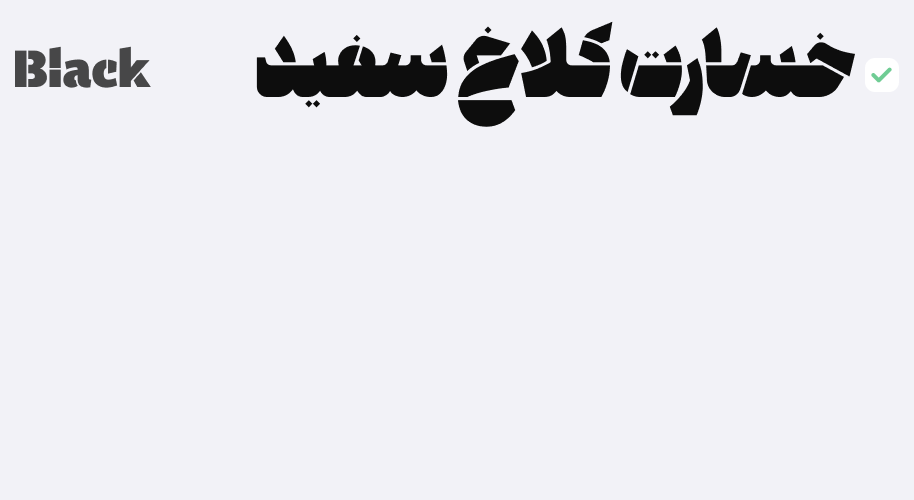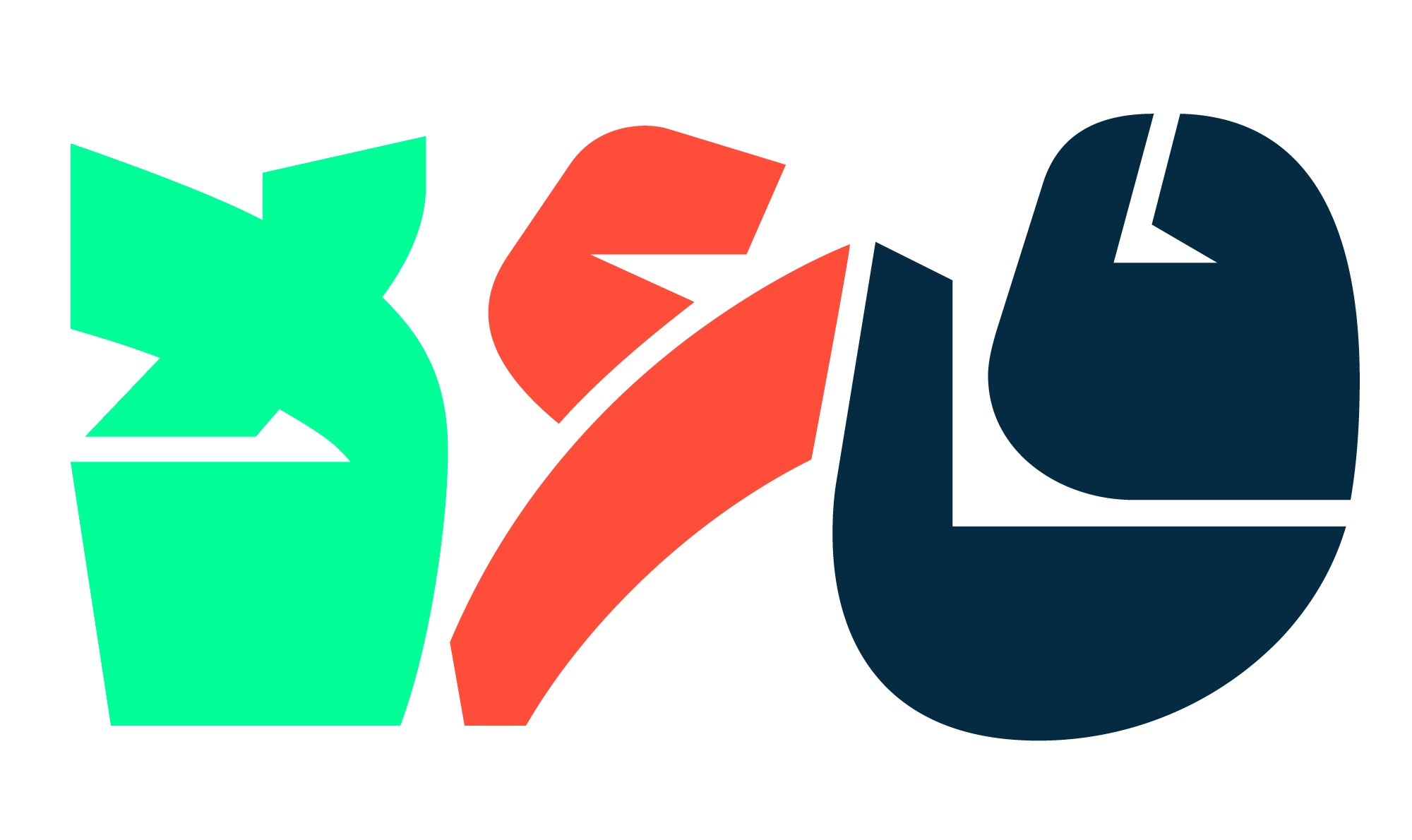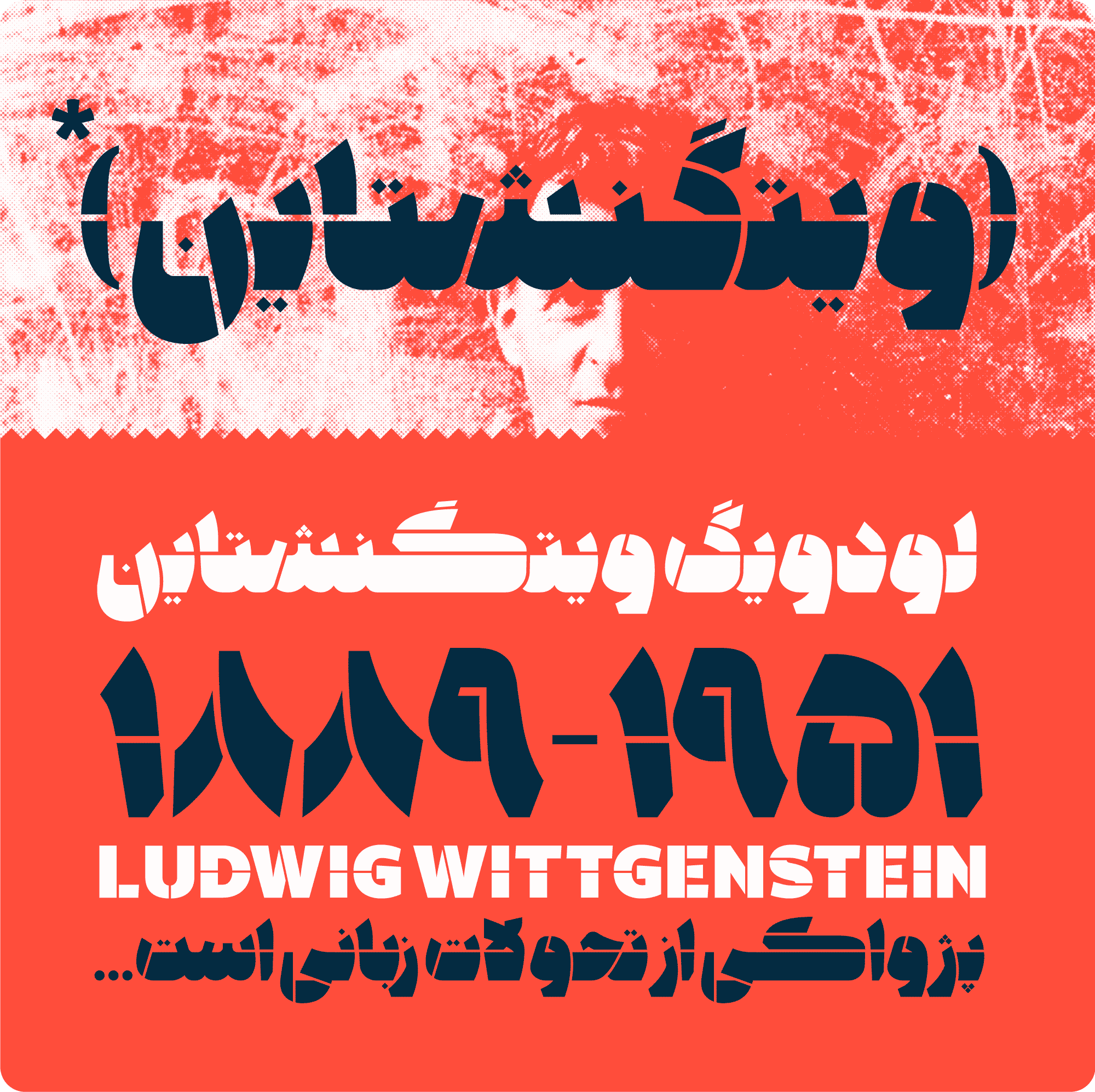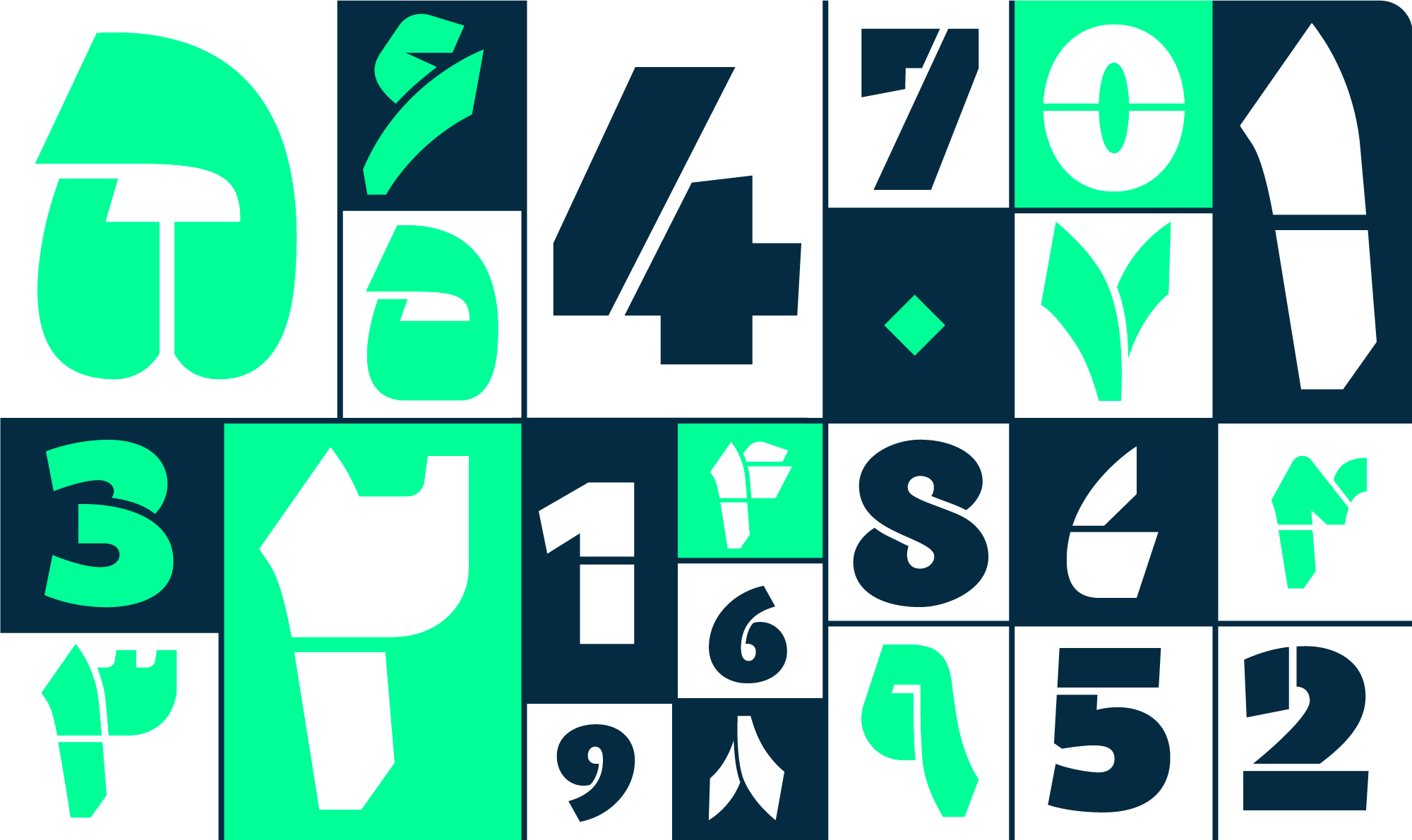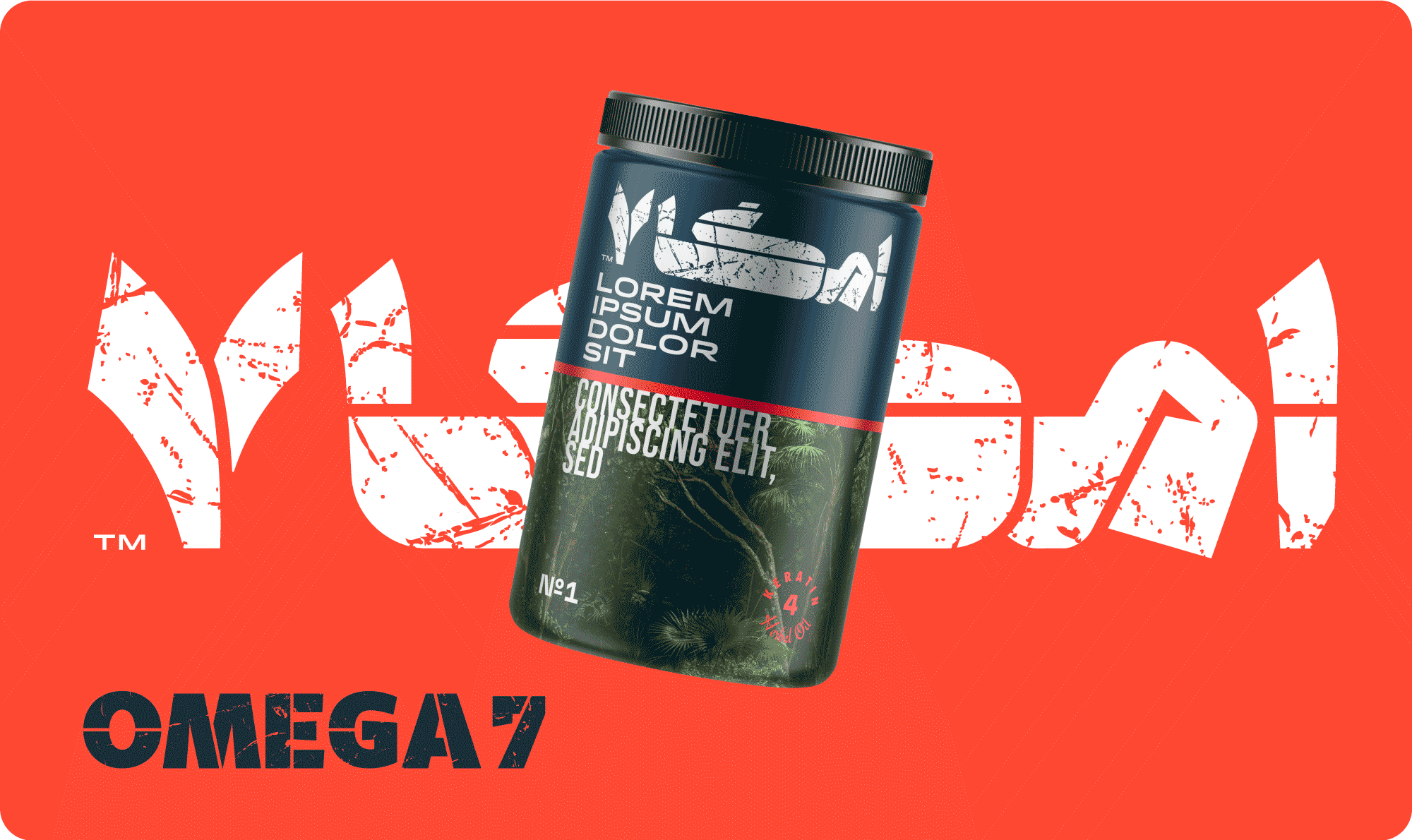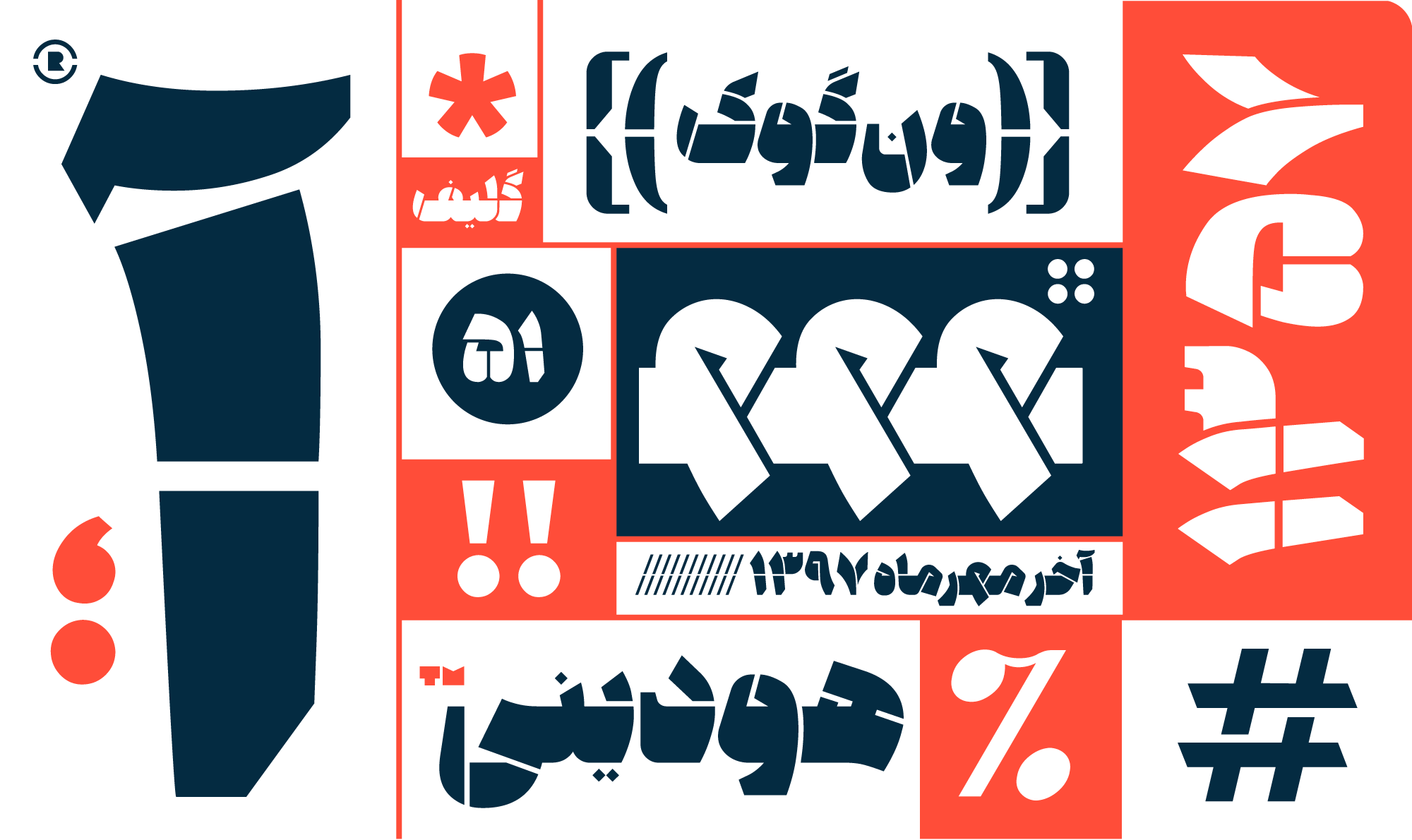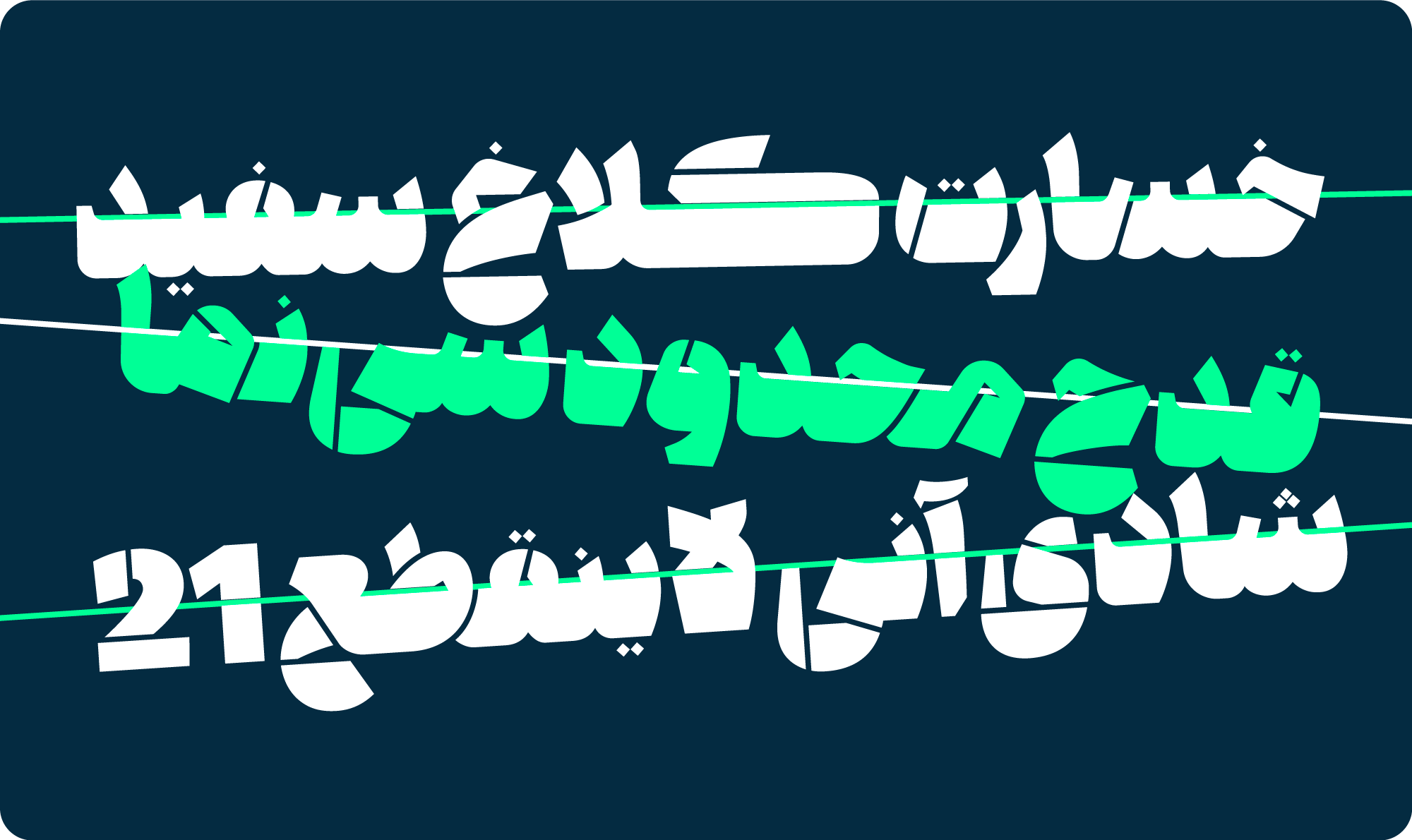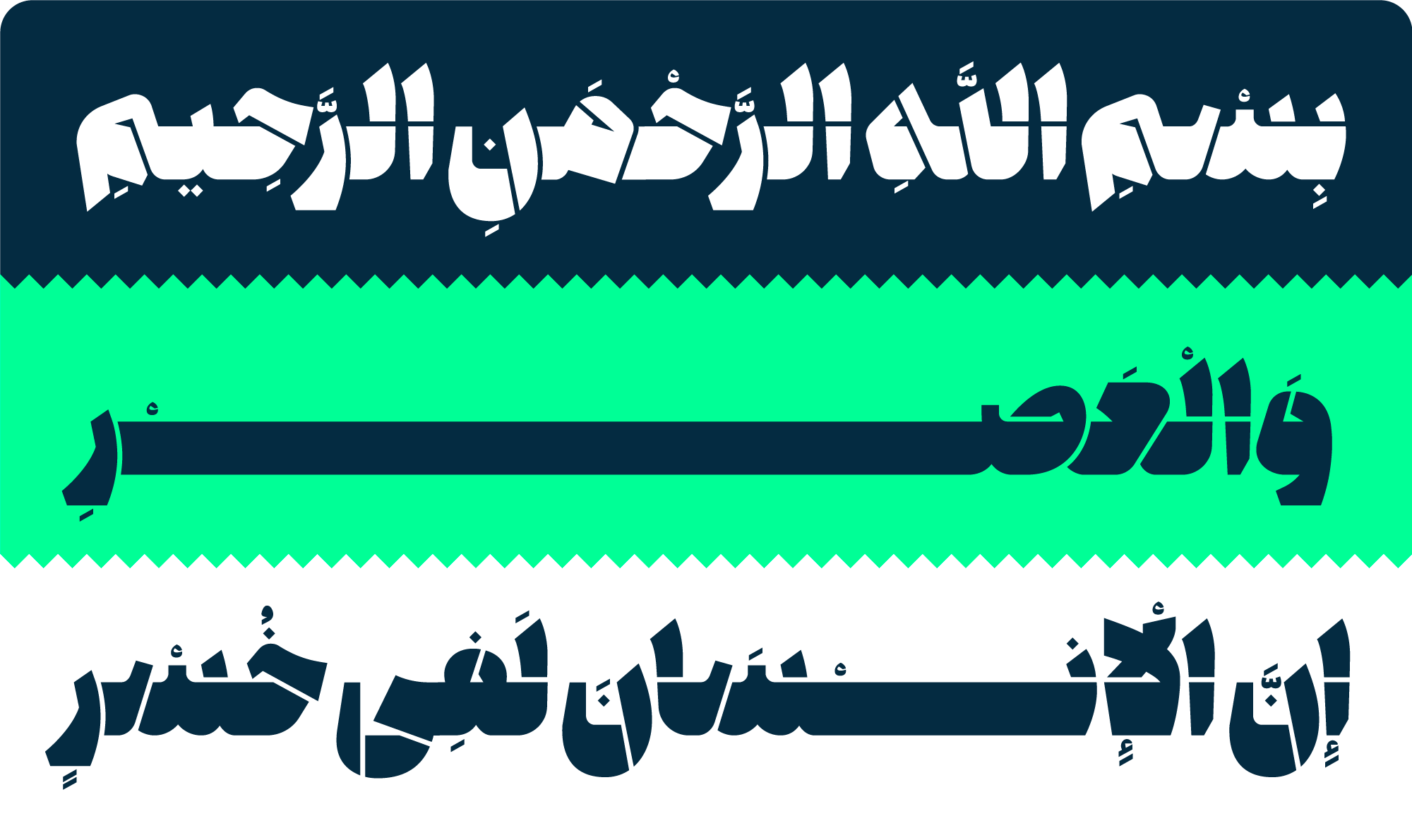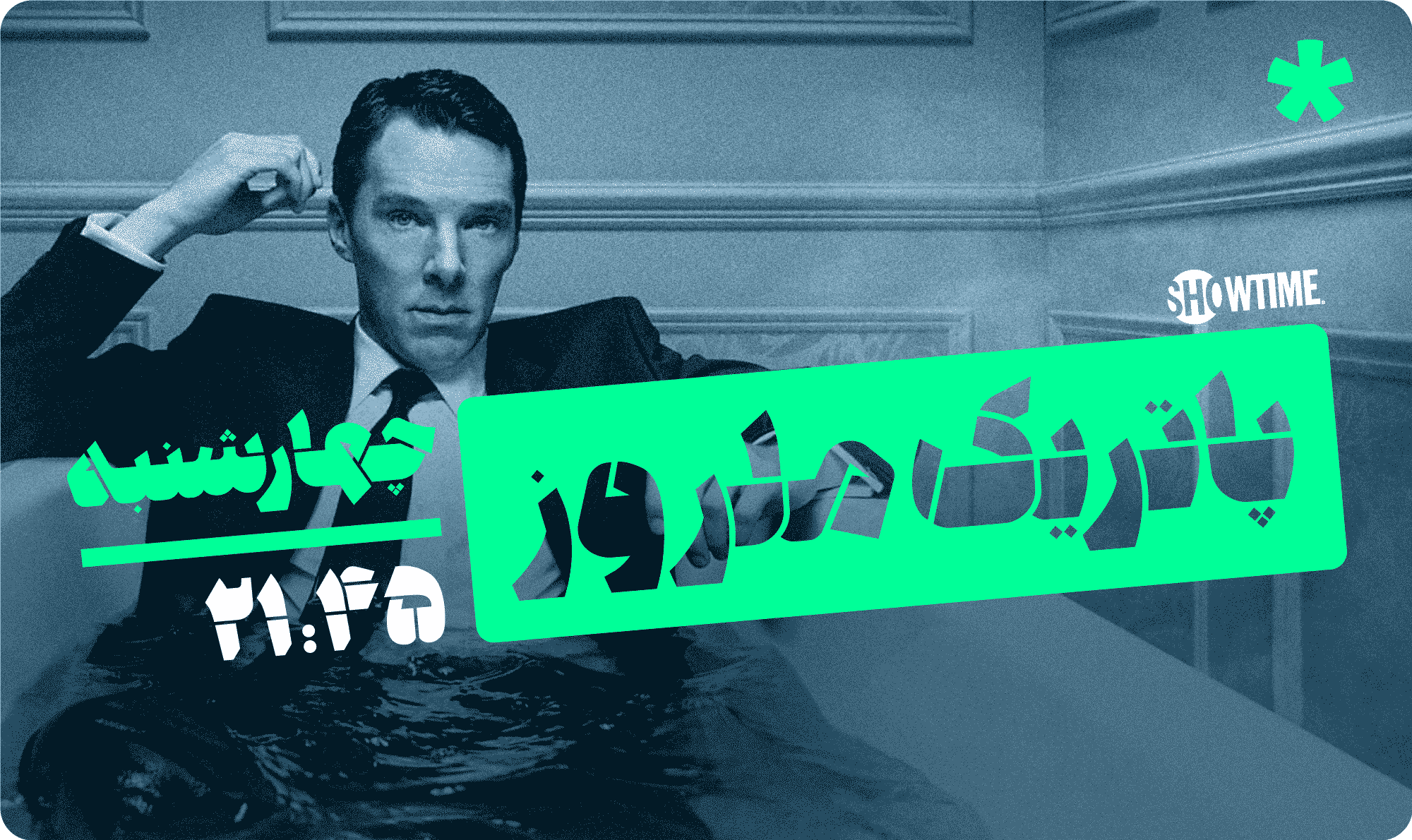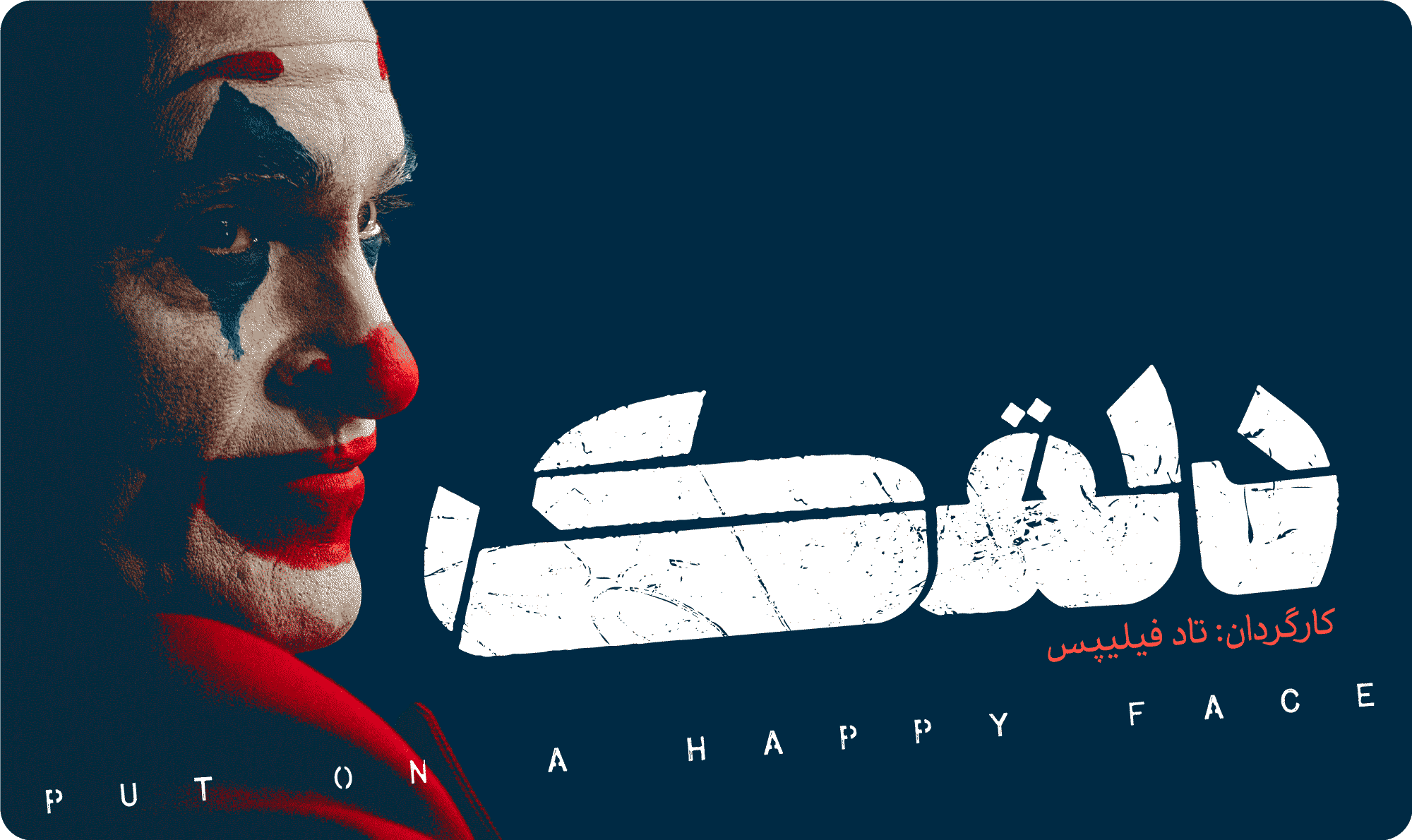
شخصیت فونت ۸۹۸ استنسیل با برشهای استنسیلی سعی دارد از حالت رسمی و سنتی که در بنمایهاش وجود دارد بگریزد و خود را در قالبهای مدرن جا کند.
فضاهای خالی در زوایای مختلف به ۸۹۸ استنسیل حرکت و پویایی میدهد، چشم را درگیر میکند، و با بازیگوشی قابلیت و ظرفیت آن را گسترش میدهد.
در طراحی تایپفیس ۸۹۸ سعی شده خلأ فونت چاق (FAT) در تایپ فارسی بر اساس نیازها و معیارهای بصری طراح برطرف شود.
فونت ۸۹۸ استنسیل قابلیت پشتیبانی از فارسی، عربی، کردی، اردو، انگلیسی و فرانسه را دارد. در نسخه لاتین از فونت (Tabac sans (Tomas Brousil استفاده شده است و به جز برش استنسیل به ضخامت فارسی هیچ تغییری در آن اعمال نشده است.
اعداد از مهمترین اجزای این فونت هستند.
مشخصه دیگر این تایپفیس مقیاس پیکرهی آن است؛ نقطهها و اعراب بسیار کوچکتر از دیگر اجزای تایپ طراحی شده تا فونت ۸۹۸ غولپیکر به چشم آید.